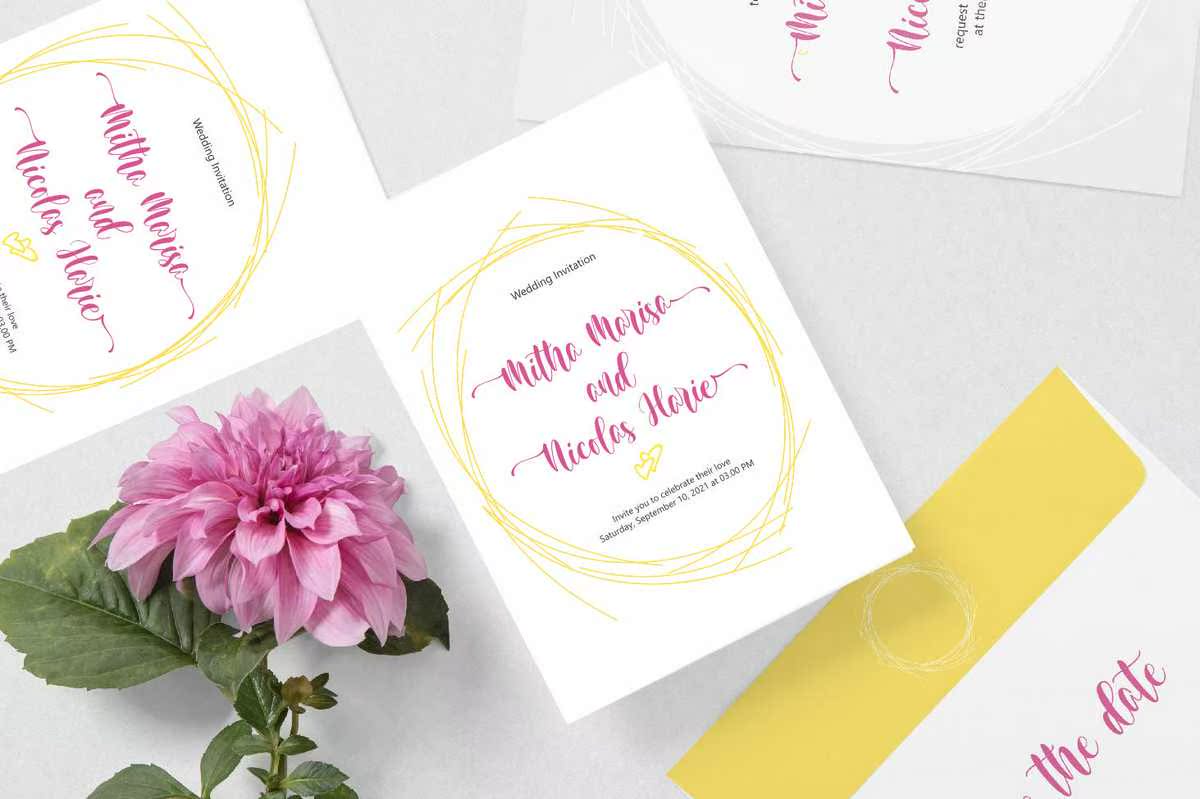
Hello Omorina是一款极具个性的卡通脚本字体。混合了手写风格的铜制字体。设计简洁优雅。令人震惊的脚本之所以吸引人,是因为它光滑、干净、女性化、性感、迷人、简单且易读。它的经典风格非常适合应用于邀请、标签、菜单等所有形式的项目,徽标、时装、化妆品、文具、凸版印刷、浪漫小说、杂志、书籍、贺卡/婚礼卡、包装、标签。他拥有极为独特的卡通脚本字体,具有极强的可替代性。混合了手写风格中的铜书法。设计为简洁优雅的风格。令人震惊的脚本之所以吸引人,是因为它光滑、干净、女性化、性感、迷人,简单易读。其经典样式非常适合应用于所有类型的正式项目,如邀请函、标签、菜单、徽标、时尚、化妆品、文具、凸版印刷、浪漫小说、杂志、书籍、贺卡/婚礼卡、包装、标签。